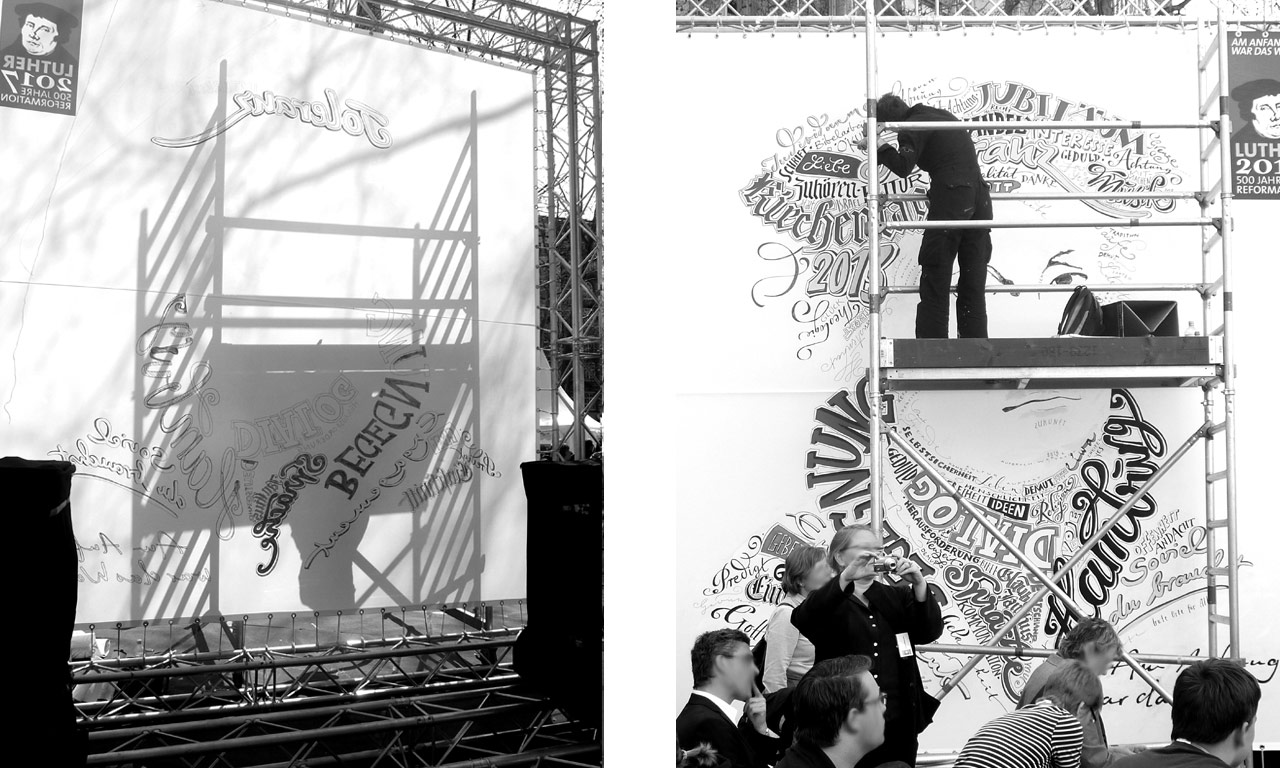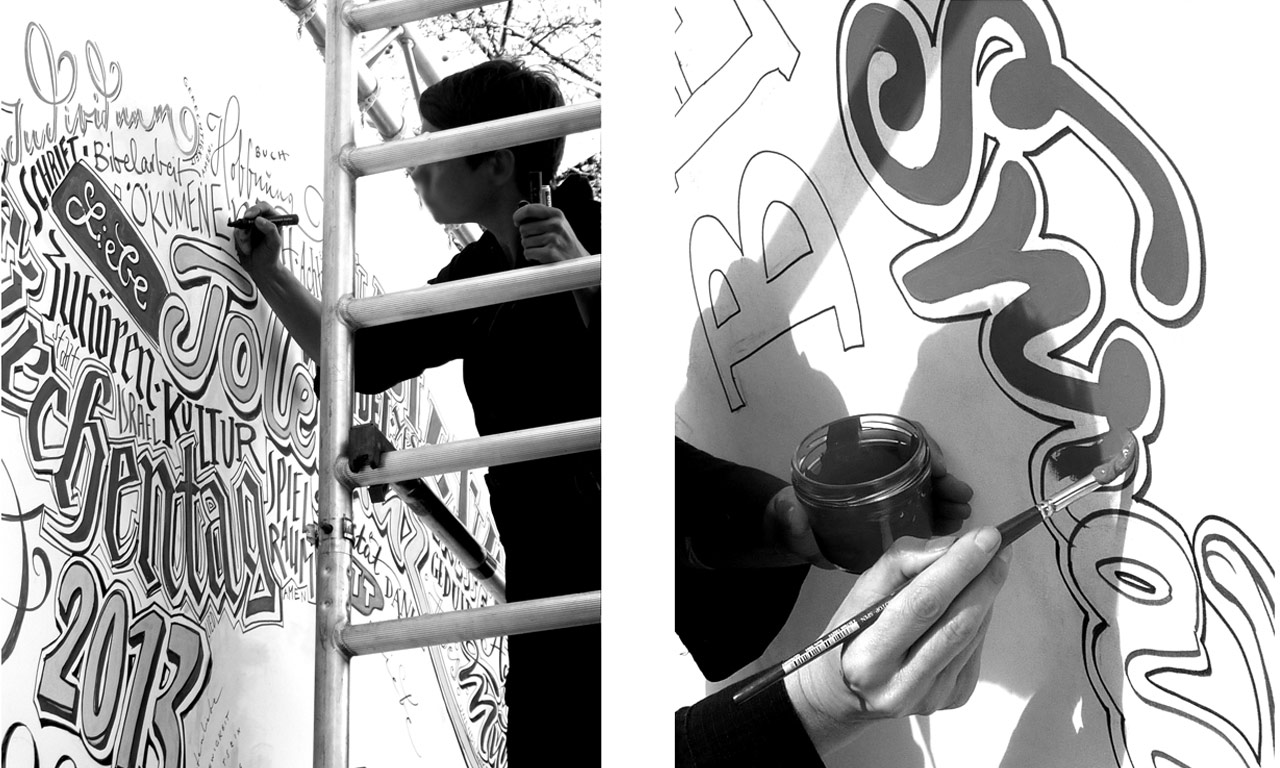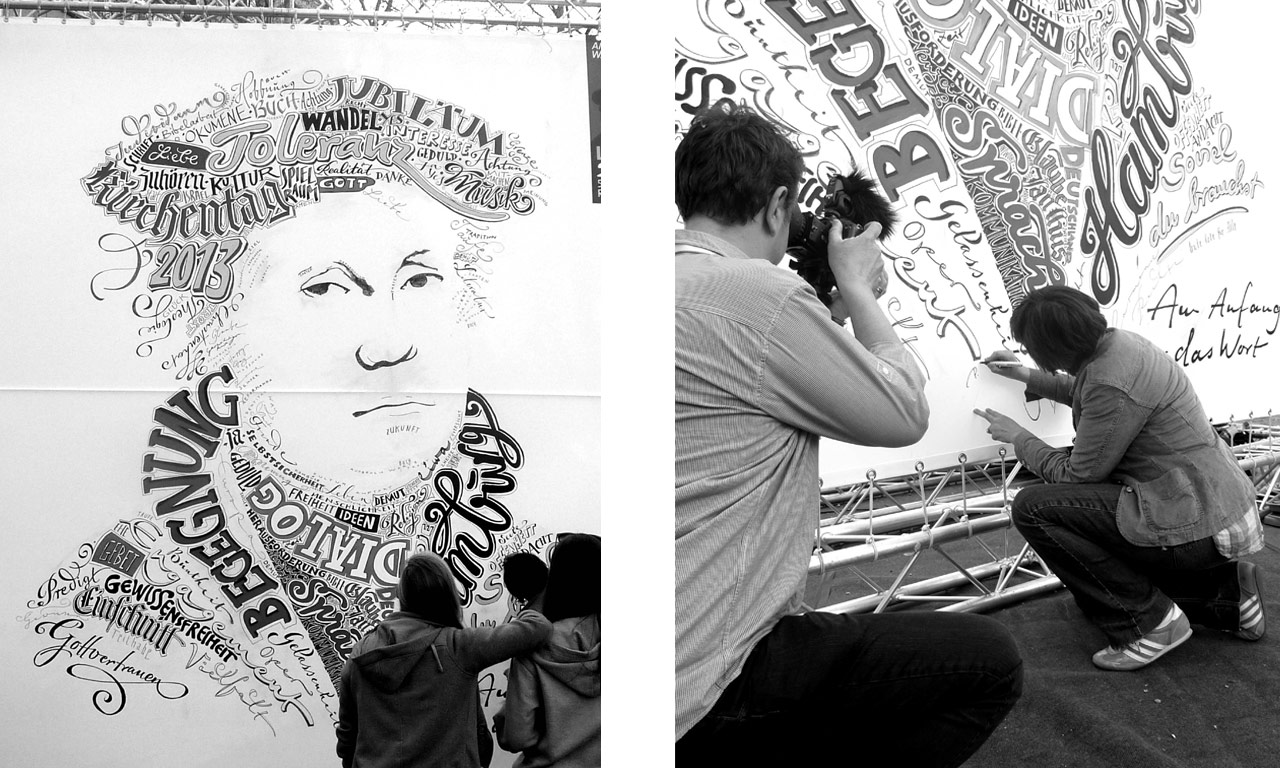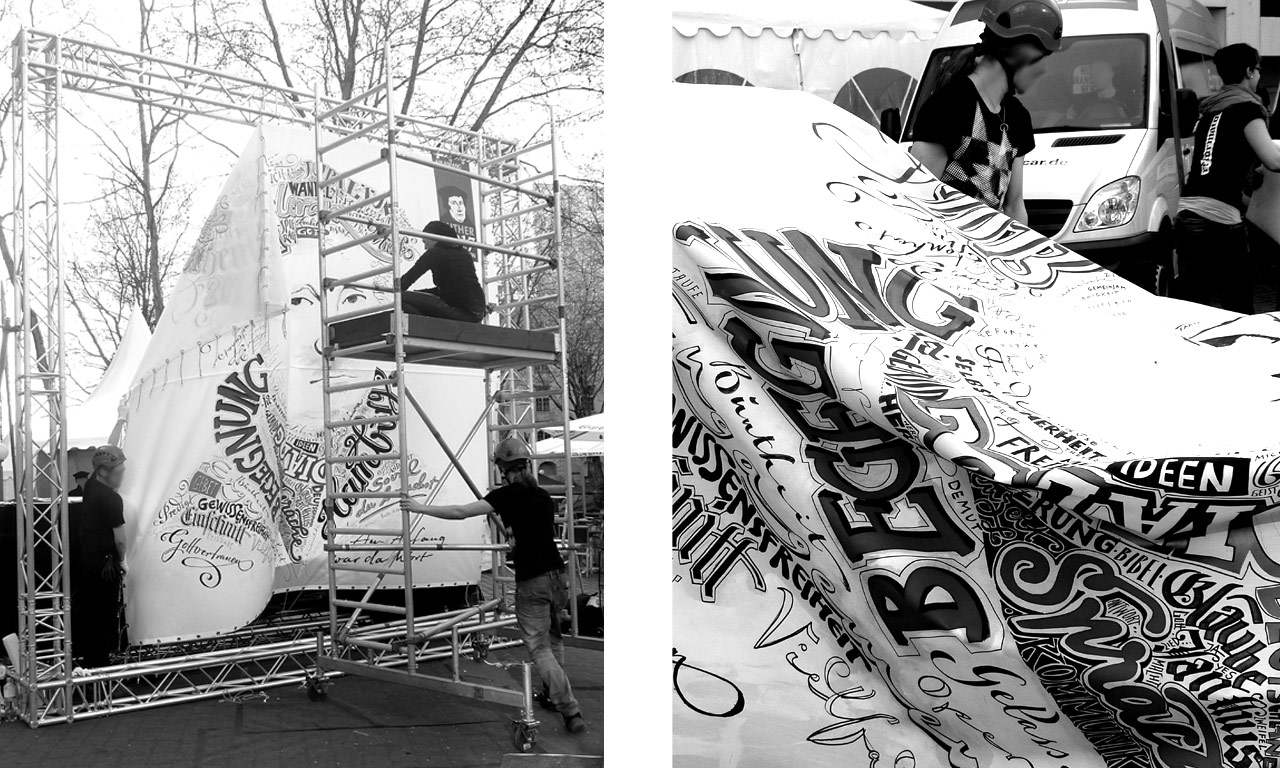
Live-Lettering, Lutherportrait
Leistung: Materialstests im Vorfeld, Live-Lettering
Am 3. und 4. Mai 2013 haben ich im Rahmen des Deutschen Evangelischen Kirchentages in Hamburg auf eine 4 x 4 Meter große Leinwand ein übergroßes Lutherporträt aus handgeschriebenen und gezeichneten Worten »live« umgesetzt. Ein Teil der Worte waren Bestandteil des Briefings. Ein Großteil der Worte jedoch kamen direkt aus dem Publikum und wurden spontan von mir auf die Leinwand gebracht, ohne vorherige Entwürfe oder Vorzeichnungen. Nach der Veranstaltung wurde die Leinwand abgebaut und in die Lutherstadt Wittenberg gebracht.